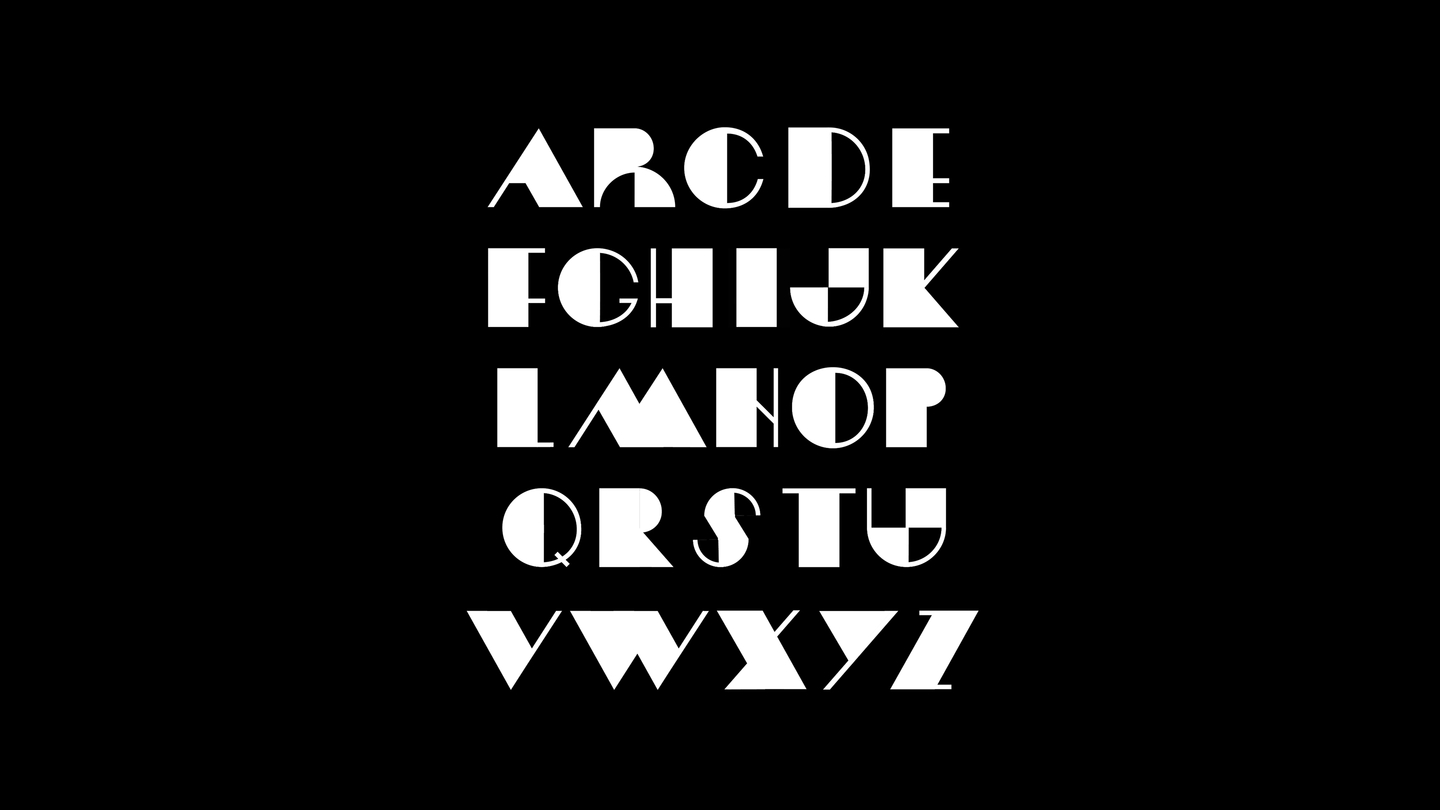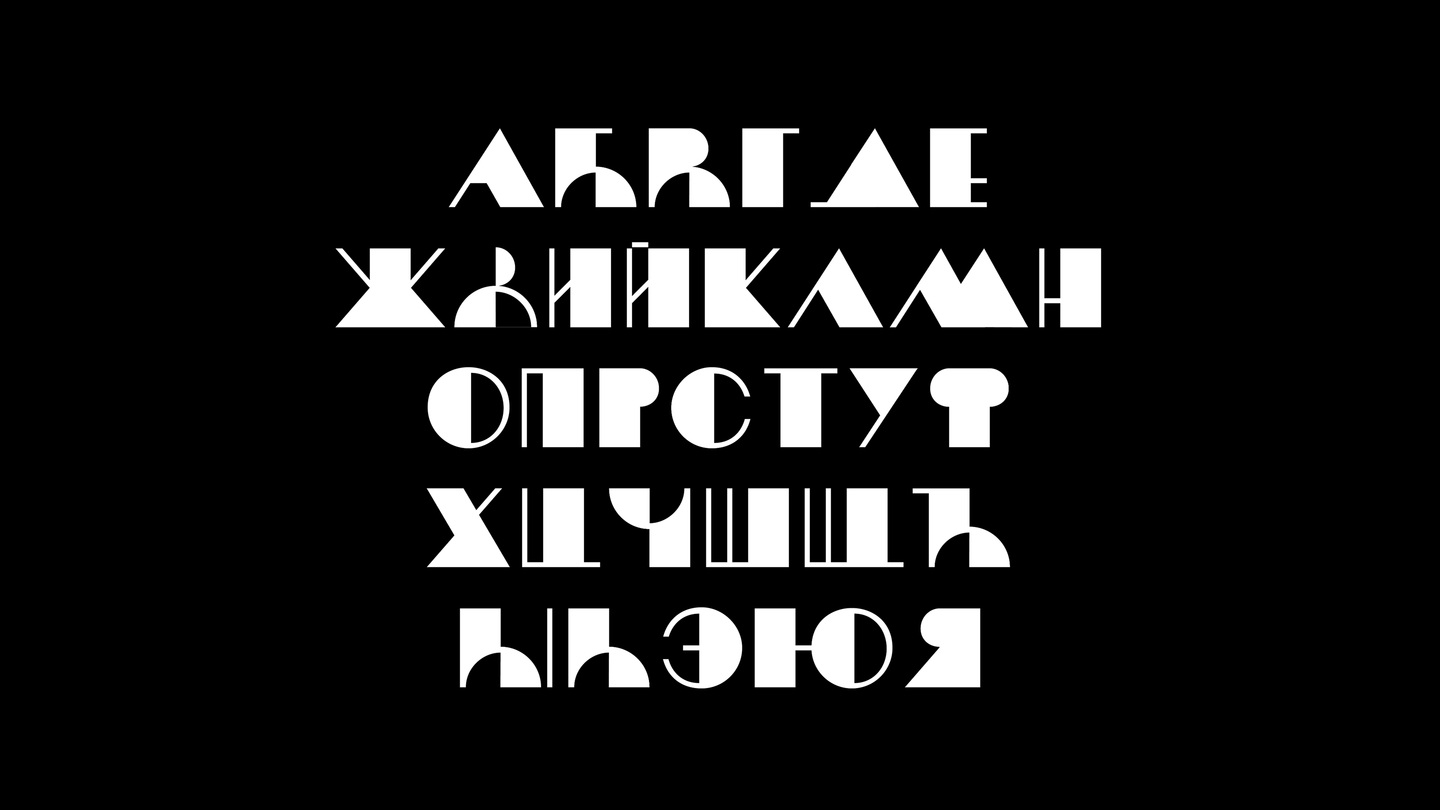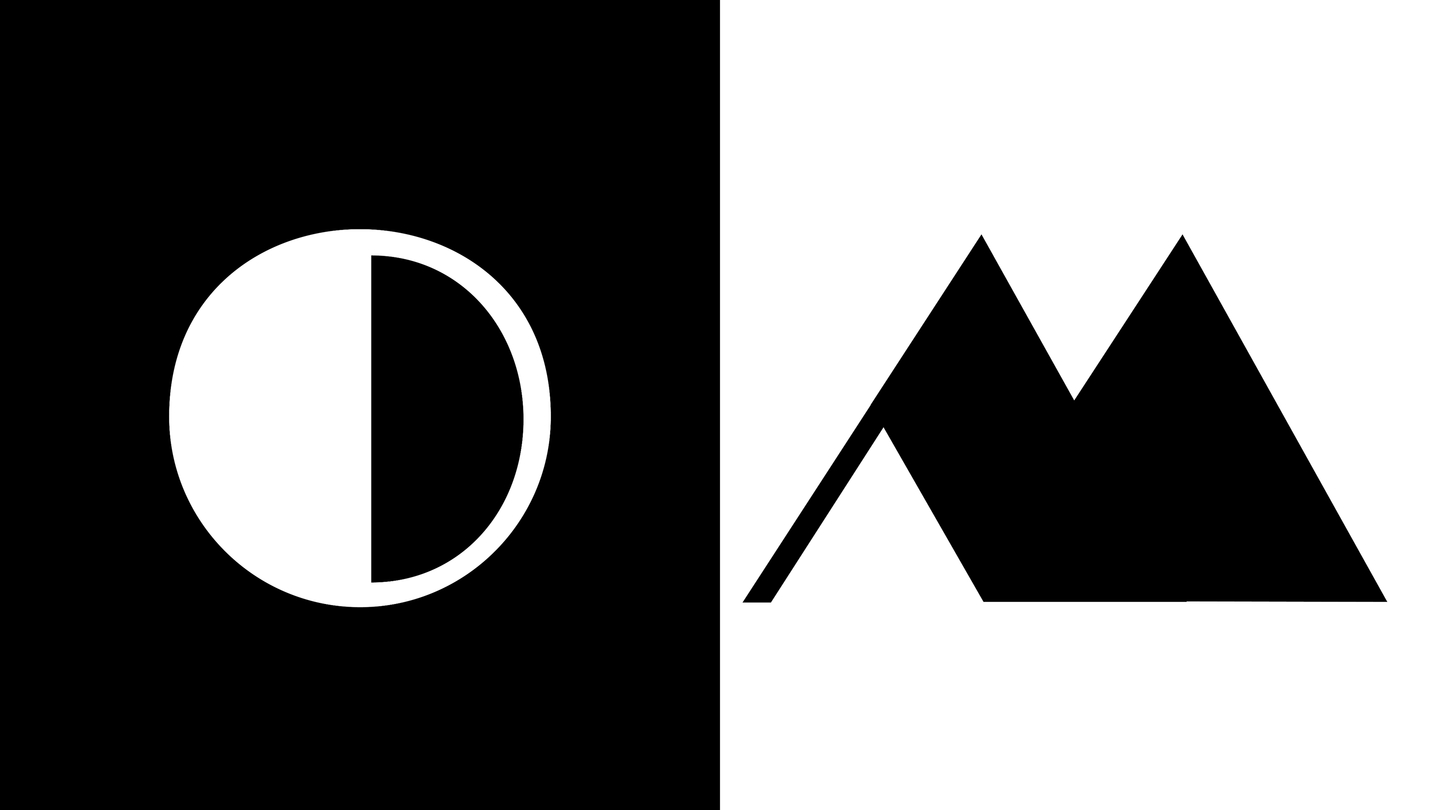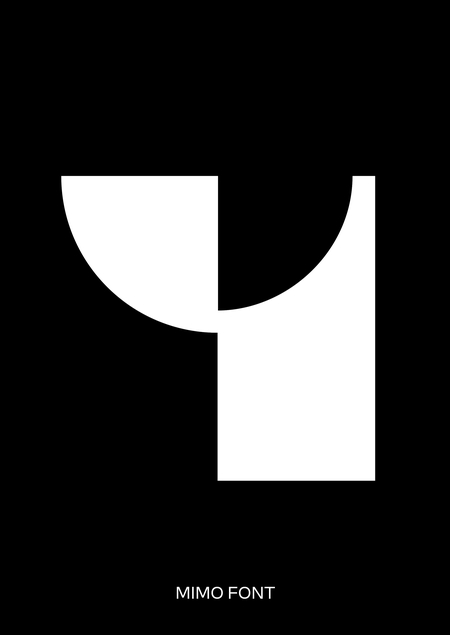
MIMO FONT
MIMO — шрифт, вдохновленный искусством пантомимы. Пластика шрифта, основанная на геометрии и контрасте, повторяет выразительные приёмы пантомимы